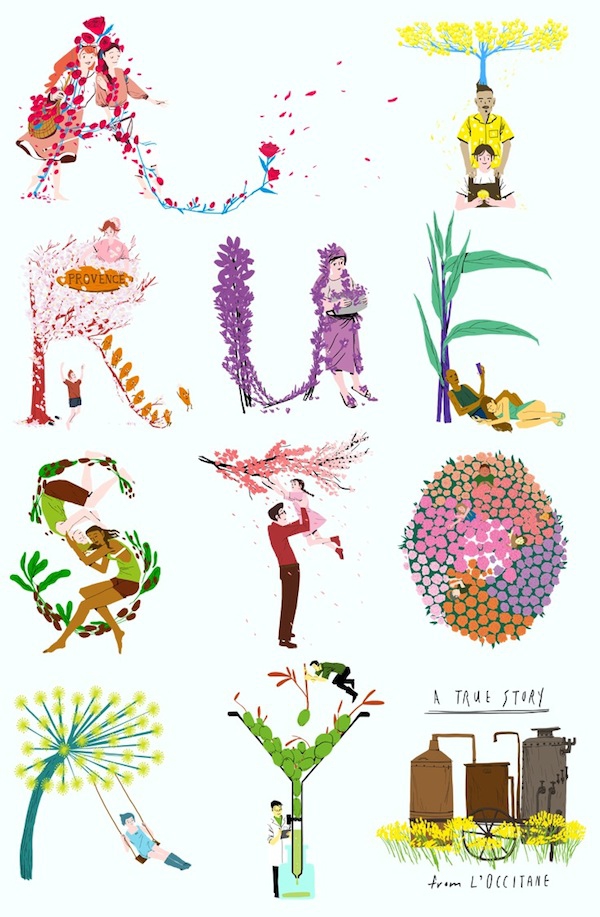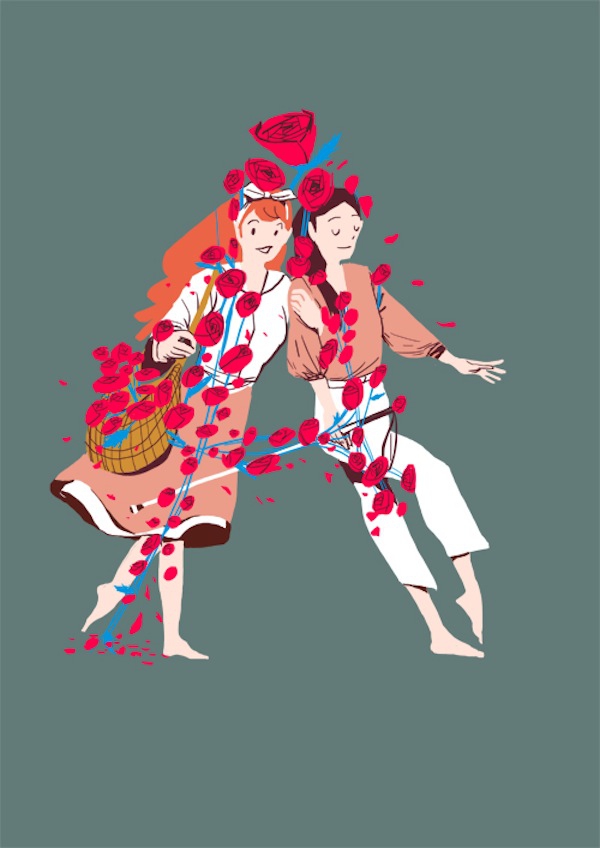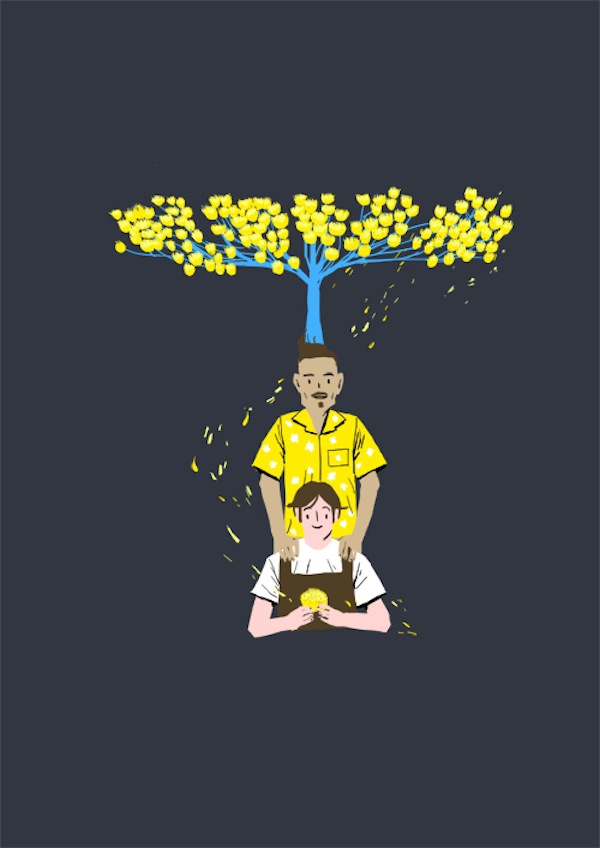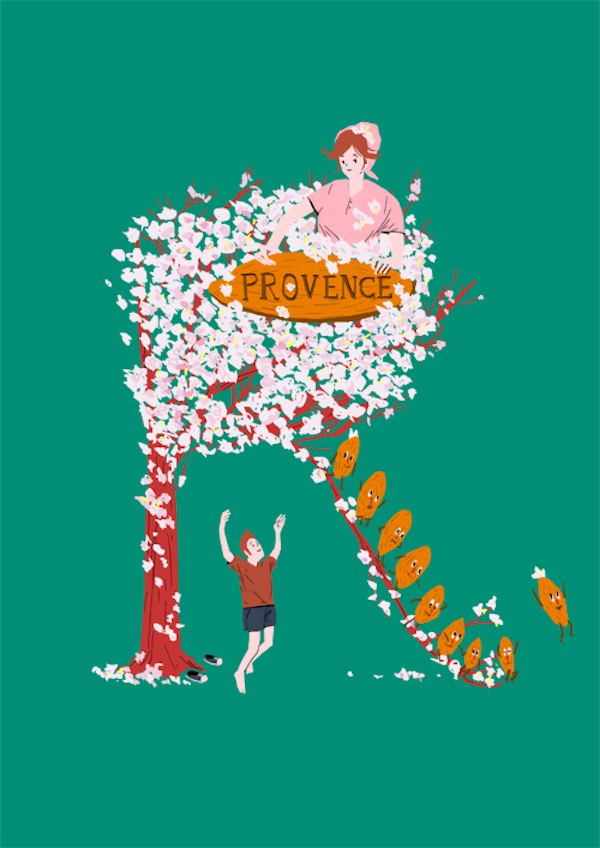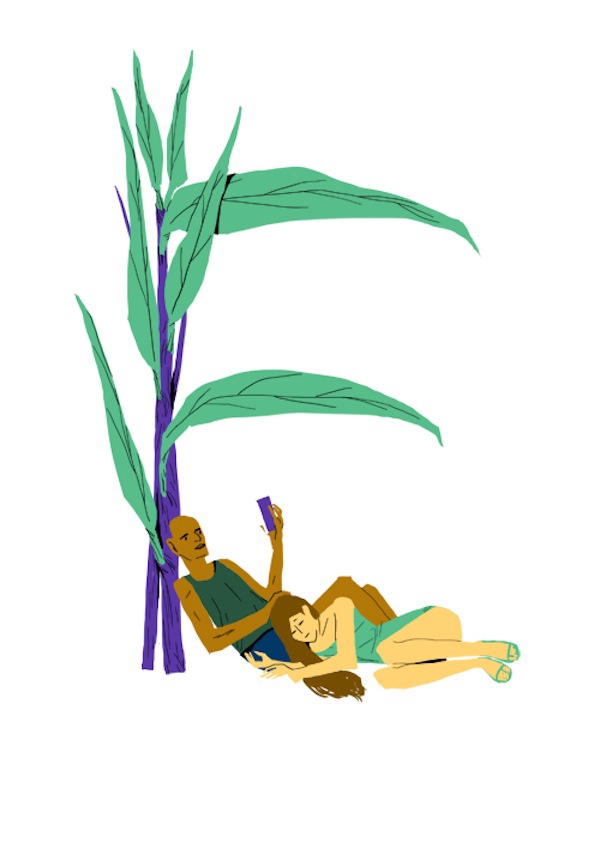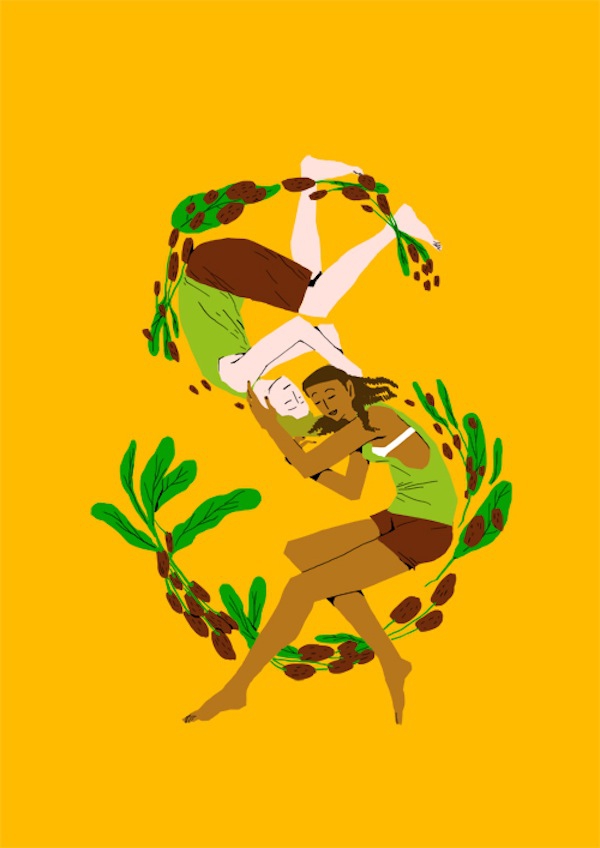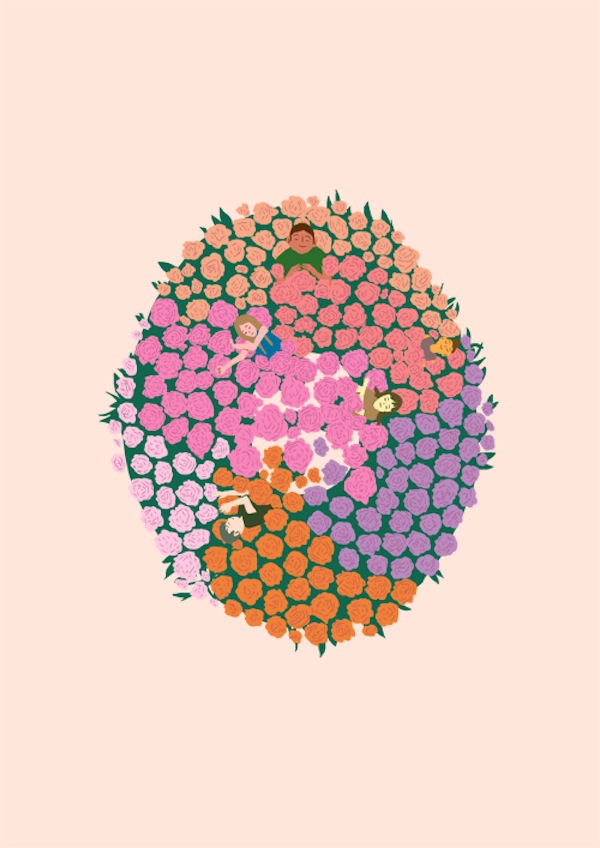
Южнокорейский иллюстратор Сид Юнг разработал оригинальный набор букв для бренда французской косметики для ухода за телом L'Occitane. Созданный при помощи изображения людей, цветов и фруктов, новый шрифт напомнит о спокойном отдыхе на природе.
Буквы для L'Occitane представлены в виде людей, которых окружают цветы, деревья, травы и фрукты. Этот природный шрифт Сид Юнг придумал после того, как услышал и проникся историей возникновения фирмы L'Occitane.
Свой первый продукт основатель L'Occitane Оливье Боссан сделал из цветка розмарина, имея на руках один лишь дистиллятор.
Новый шрифт, по мнению Сида Юнга, должен напоминать людям о беззаботной сельской жизни и успокаивать. Новое решение для бренда было представлено в рамках кампании «Green Allure», которая проводилась L’Occitane en Provence совместно с корейским журналом «ALLURE».